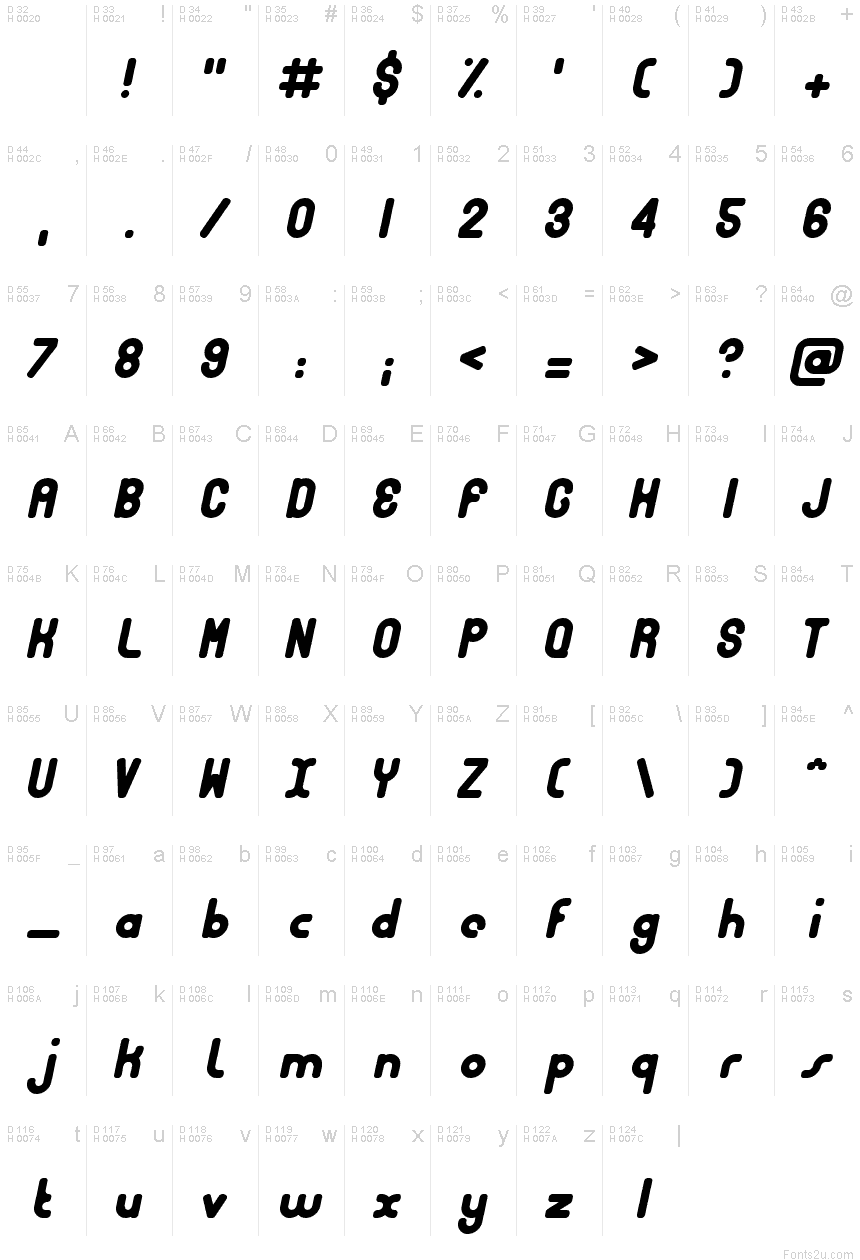
Bubble Club Italic ist eine kostenlose Comic-Display-Schrift mit einer weichen, aufgeblähten Neigung, die verspielt und ein wenig retro wirkt. Die Buchstaben sehen eher gegossen als gezeichnet aus, mit klobigen, abgerundeten Formen, einer stetigen Neigung nach vorne und großen Zwischenräumen, die die luftige Stimmung bewahren, ohne steif zu wirken.
Sie eignet sich hervorragend für Plakatüberschriften, Flyer für Kinderveranstaltungen, Süßigkeiten- oder Snackverpackungen, Zine-Cover und kurze Social-Media-Grafiken, bei denen eine kostenlose Schrift einen freundlichen Schwung braucht. Verwenden Sie sie für Titelkarten, Logo-Entwürfe oder markante Zitate, wenn Sie möchten, dass die Neigung und die aufgeblasenen Formen die meiste Arbeit übernehmen.